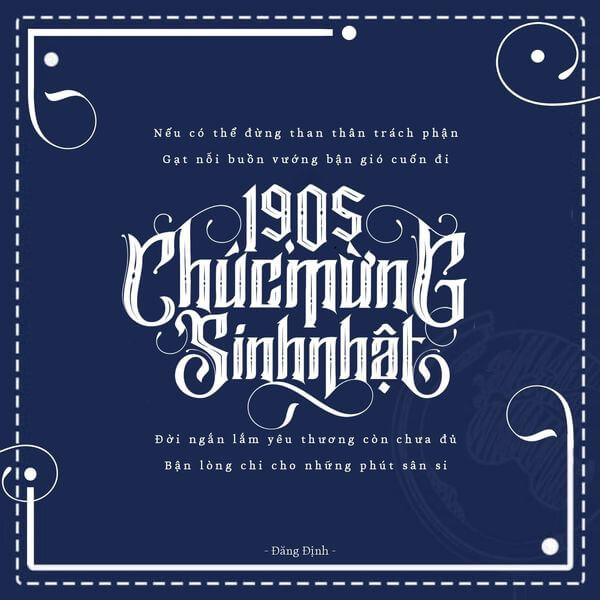
Font Gothic Việt hóa (thường được biết đến là dòng chữ Blackletter hoặc phông chữ cổ điển thời Trung cổ) là nhóm phông chữ mang phong cách huyền bí, gai góc và đậm chất quyền lực vương giả châu Âu. Với những đường nét cắt gọt góc cạnh mô phỏng nét bút lông ngòi dẹt dứt khoát cùng tỷ lệ chữ đặc quánh, phông chữ này là lựa chọn số một cho các thiết kế nhãn bia thủ công, bao bì rượu mạnh, thời trang Streetwear cá tính và các ấn phẩm phong cách Dark Romance. Doozypack.vn cung cấp link tải font Gothic Việt hóa chuẩn kỹ thuật, giúp bạn sở hữu kho phông chữ ma mị độc đáo mà không lo gặp bất kỳ lỗi hiển thị dấu thanh nào khi thiết kế in ấn.
Đặc điểm thẩm mỹ độc đáo của các dòng font Gothic
Gothic không đi theo sự thanh mảnh của các phông chữ hiện đại; nó tái hiện trọn vẹn sự uy nghiêm, bí ẩn và chiều sâu lịch sử của những bản thảo chép tay từ thế kỷ 12.
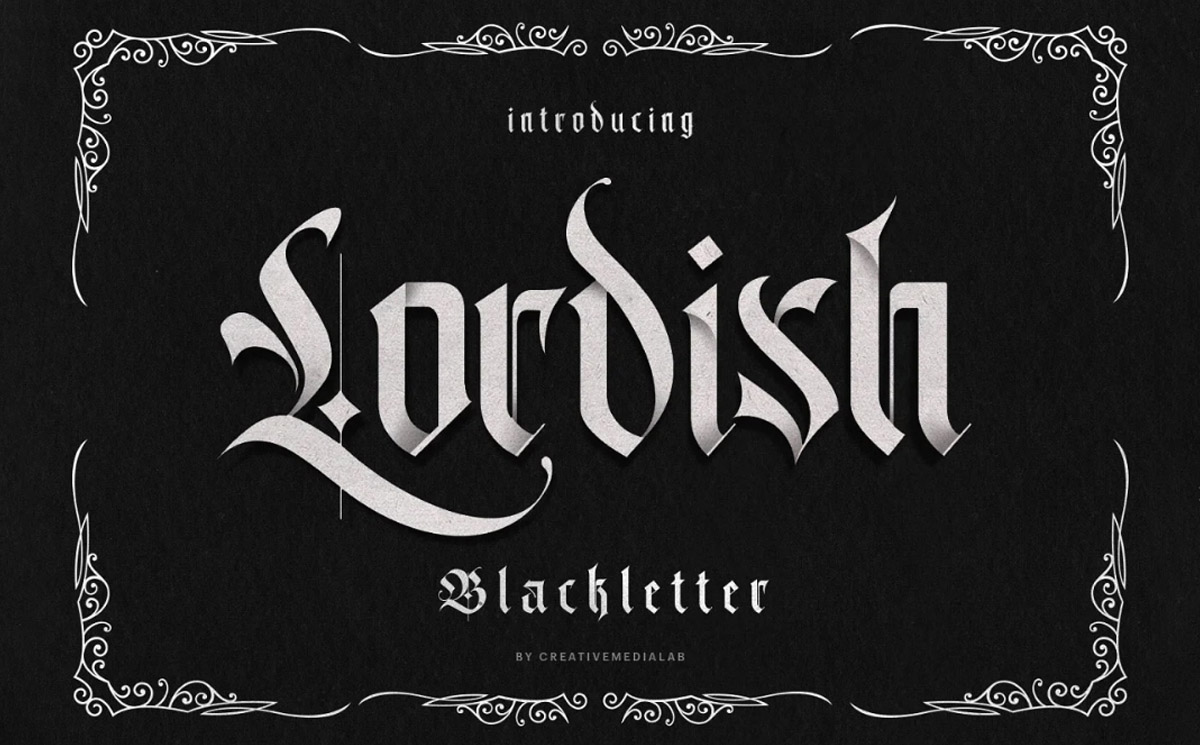
Phong cách Blackletter trung cổ huyền bí và đầy quyền lực
Đặc trưng lớn nhất của font Gothic Việt hóa là cấu trúc chữ dày đặc với các nét dọc thẳng tắp kết hợp cùng các góc nhọn hình thoi hoặc hình tam giác ở đầu và chân chữ. Bố cục của từng con chữ mô phỏng lại những ô cửa sổ vòm nhọn trong kiến trúc nhà thờ Gothic cổ kính. Khi đặt phông chữ này làm tiêu đề trên bao bì, thương hiệu của bạn sẽ ngay lập tức toát lên diện mạo gai góc, nổi loạn nhưng vô cùng đẳng cấp, tạo dựng sức hút thị giác dữ dội đối với giới trẻ và những người yêu thích văn hóa Underground.
Đường nét điêu khắc góc cạnh với độ tương phản mãnh liệt
Các ký tự trong bộ font Gothic đẹp sở hữu sự đối lập tột cùng giữa những mảng mực đen đậm đà và các đường gạch nối thanh mảnh. Nhịp điệu Typography đan cài phức tạp biến mỗi dòng tiêu đề thành một tác phẩm nghệ thuật chạm khắc công phu, cực kỳ ăn ý với các sản phẩm mang hơi hướng cổ điển, nam tính và mạnh mẽ.
Ưu điểm nổi bật của bản font Gothic đẹp đã Việt hóa
Khi ứng dụng các phông chữ Trung cổ phức tạp vào thị trường trong nước, sự chỉn chu về dấu câu là yếu tố quyết định đến tính chuyên nghiệp của bản thiết kế:
- Khắc phục triệt để lỗi dấu tiếng Việt: Phiên bản Việt hóa đã được đội ngũ thiết kế trau chuốt thủ công từng dấu câu. Các dấu sắc, huyền, hỏi, ngã, nặng được vẽ với các góc nhọn và độ dày đồng điệu cùng thân chữ gốc, không gây cảm giác chắp vá hay đè nét làm biến dạng cấu trúc chữ.
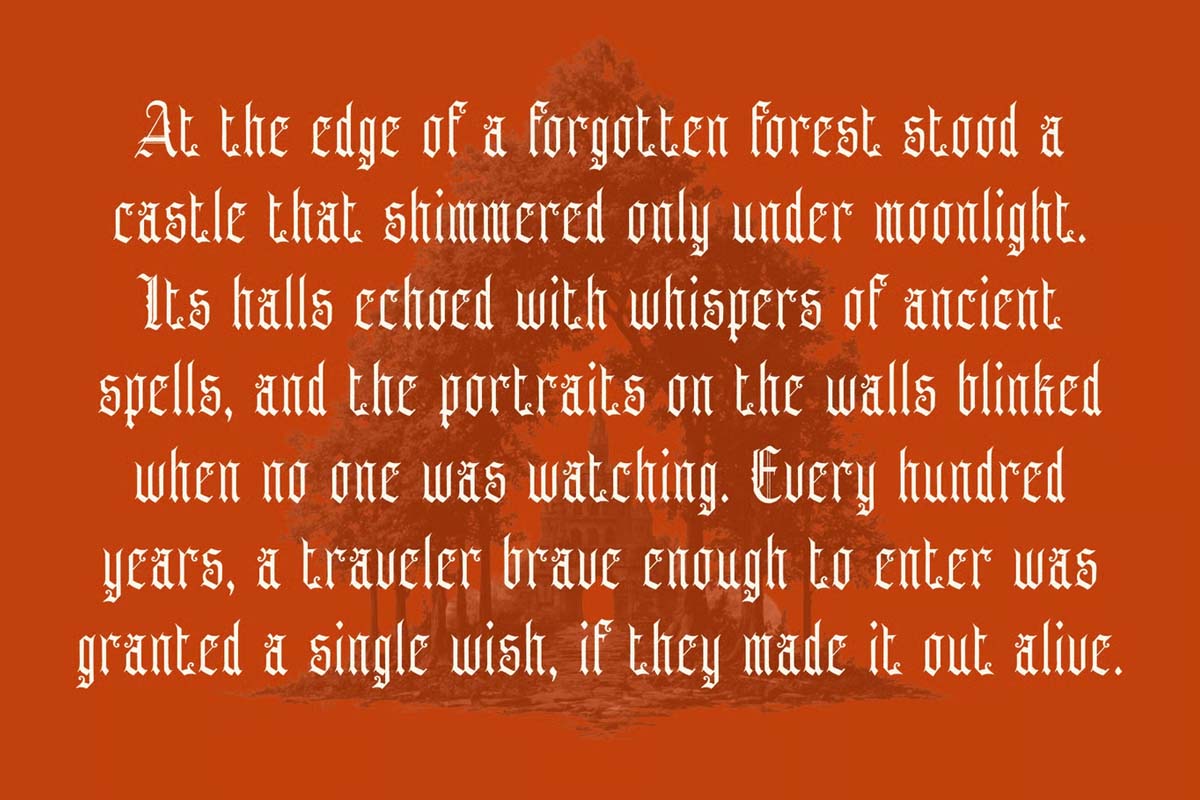
| Nhóm Font | Đặc điểm thị giác | Ứng dụng đề xuất tại Doozypack.vn |
| Gothic Textura / Fraktur | Cổ điển, góc cạnh, sắc nhọn | Nhãn chai bia thủ công, bao bì rượu mạnh, hộp Socola đen. |
| Modern Gothic Streetwear | Dày bản, cá tính, nổi loạn | Tiêu đề túi giấy thời trang, bao bì phụ kiện biker, nón bảo hiểm. |
| Gothic Ornamental | Hoa mỹ, chạm khắc cầu kỳ | Bìa sách nghệ thuật, thiệp mời Halloween, hộp quà tặng di sản. |
Ứng dụng thực tế của font Gothic trong sản xuất bao bì tại Doozypack.vn
Sự sắc lạnh và uy quyền của font Gothic mang lại hiệu ứng thị giác đắt giá trên các dòng sản phẩm bao bì thực tế do Doozypack.vn sản xuất:
- Nhãn dán chai Bia thủ công (Craft Beer) & Rượu mạnh: Tiêu đề thương hiệu in bằng font Gothic kết hợp kỹ thuật ép kim nhũ đồng trên giấy decal kháng nước tạo nên diện mạo vô cùng đẳng cấp và nam tính.
- Hộp giấy thời trang Streetwear & Tattoo Care: Nét chữ góc cạnh mô phỏng hình xăm nghệ thuật, giúp bao bì toát lên vẻ nổi loạn, độc bản và đậm chất văn hóa đường phố.
- Bao bì Socola đen & Nến thơm Gothic: Sự kết hợp giữa font Gothic và nền hộp giấy tối màu mang lại cảm giác bí ẩn, quyến rũ và khơi gợi sự tò mò của người tiêu dùng.